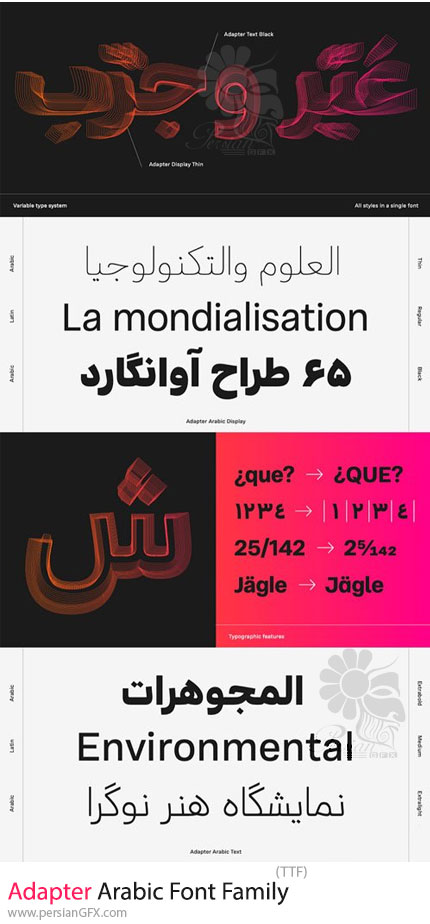
در این بخش شاهد فارسی و عربی آداپتر می باشید که با فرمت های TTF و JPG بر روی سایت برای دانلود قرار گرفته است. فونت فارسی و عربی آداپتر یک مجموعه منحصر به فرد و چندمنظوره است که برای پاسخگویی به نیازهای طراحی مدرن و معاصر ایجاد شده است. این فونت توسط طراح برجسته، برنا ایزدپناه، طراحی شده و در اختیار طراحان قرار گرفته تا تجربهای جدید و جذاب از تایپوگرافی عربی و فارسی ارائه دهد. فونت آداپتر با الهام از دو رویکرد متفاوت در تایپوگرافی طراحی شده است. این فونت هم برای متون پیوسته (Continuous Text) و هم برای طرحهای برجسته مانند پوسترها و جلد کتابها مناسب است. این فونت تمامی حروف و علائم نگارشی مورد نیاز برای زبانهای فارسی، عربی و اردو را پشتیبانی میکند و به طور کامل با ساختار این زبانها سازگار است. فونت آداپتر به خوبی نیازهای طراحیهای مدرن را پوشش میدهد و گزینه مناسبی برای طراحانی است که به دنبال فونتی هستند که هم در طراحی رسمی و هم در طرحهای خلاقانه کاربرد داشته باشد. فونت آداپتر عربی و فارسی یک انتخاب ایدهآل برای طراحانی است که به دنبال تایپفیس چندمنظوره با خوانایی بالا و زیباییشناسی مدرن هستند. این فونت میتواند تجربه بصری منحصر به فردی برای پروژههای متنی و گرافیکی ایجاد کند و در عین حال احترام به خوانایی و ساختار زبانهای فارسی و عربی را حفظ میکند.